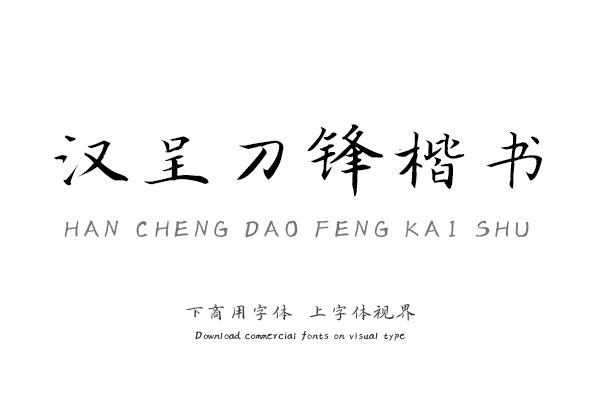
汉呈字库由书法家王天喜先生在2018年创立于互联网之都,G20之都中国杭州,致力于传承中华文字之美,将传统书法艺术与互联网技术以及区块链技术相结合,致力于打造中华互联网字体库著名品牌。汉呈字体库的创始团队毕业于中国美院、中央美院、浙江大学等高校,并拥有多年供职于华为、阿里巴巴、网易等世界一流科技公司的经验,拥有雄厚的技术积累。
汉呈刀锋楷书字体是汉呈字库推出的一款个性行楷字体,字体书写颇具个性,整体效果非常美观大方,其在传统行楷字体上进行了艺术创新,让字体整体效果看上去更出彩,且具有很好的视觉感。